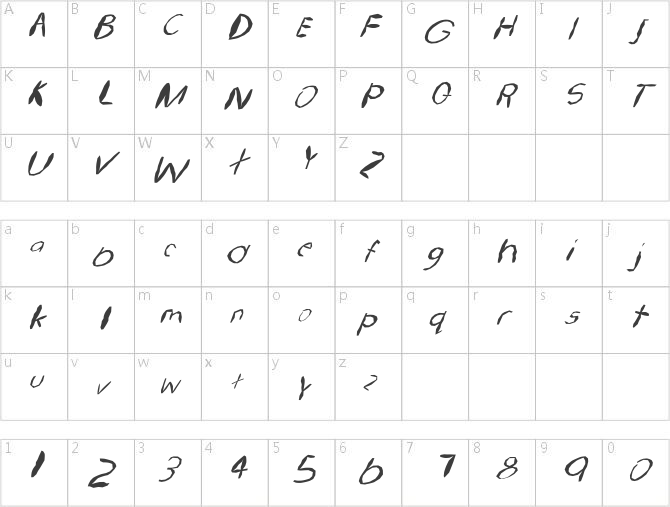
FZ HAND 22 MANGLED ITALIC
FZ HAND 22 MANGLED ITALIC介绍
FZ HAND 22 MANGLED ITALIC字体字库是一款让人赏心悦目、百看不厌的英文字体,适合各类广告和产品包装设计应用,字体大小0.05MB,格式为ttf字体,上传用户是文生电脑,作者/版权方为未知
FZ HAND 22 MANGLED ITALIC效果图